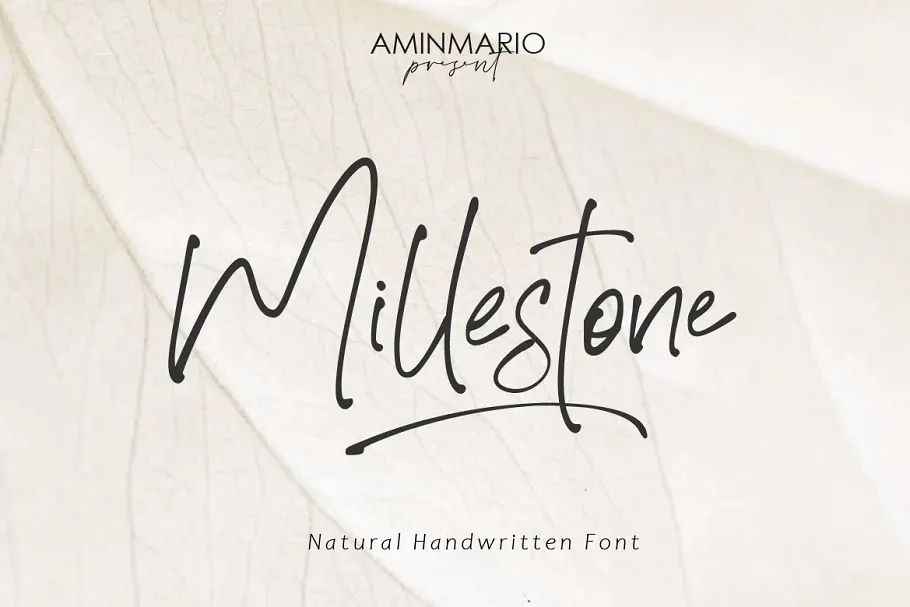
Esta fonte ‘Millestone Font’ é uma tipografia de script escrita à mão que foi projetada para imitar a expressão genuína do traçado humano. Desenvolvida pelo estúdio sartstudio, esta fonte incorpora alternativas para letras minúsculas e ligaturas, assim como sublinhados, permitindo-a atingir um aspecto natural muito próximo à escrita à mão de quem a usa. Feita em estilo OpenType, ela oferece uma experiência imersiva de escrita, tornando-se quase palpável ao usar. Seja para criar cartões personalizados ou gráficos de newsletter, esta fonte é perfeita para aqueles que desejam incorporar um toque autêntico e emocionante em seus projetos digitais.